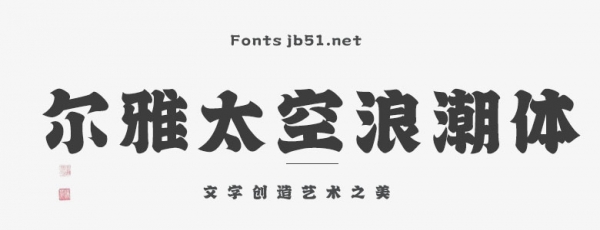
爾雅太空浪潮體是一款霸氣中國(guó)風(fēng)楷體,適合應(yīng)用于藝術(shù)設(shè)計(jì)、平面宣傳設(shè)計(jì)、網(wǎng)頁(yè)設(shè)計(jì)、書(shū)法字體,海報(bào)設(shè)計(jì)等領(lǐng)域,歡迎喜歡這款字體的朋友下載收藏。